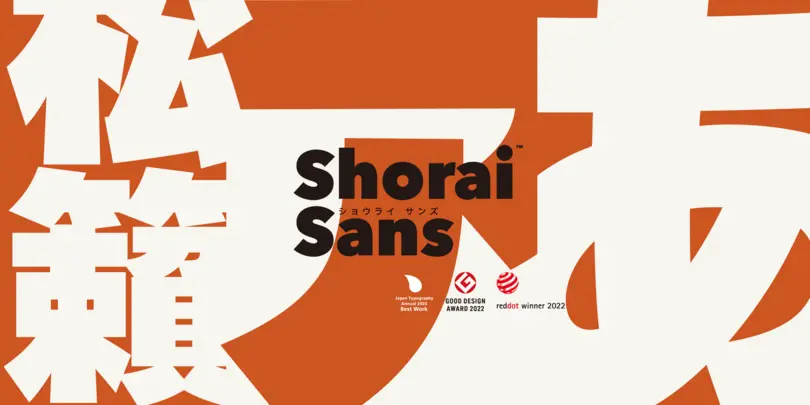
Shorai Sans:何も足さない「素」のかたち
Avenir Nextと調和する日本語書体
Shorai Sansは、欧文書体「Avenir Next」の造形的な特徴を取り入れて開発された日本語サンセリフ体です。「何も足さない『素』のかたち」をコンセプトに、文字の骨格を極限まで単純化し、均一な線とすっきりとした形状を追求しました。幾何学的な美しさを持ちながらも、人の手で書いたような自然な温かみを感じさせるデザインが特徴です。
付属欧文には、日本語の文字に合わせてサイズや位置を調整したAvenir Nextを採用。和文と欧文を別々に選ぶ必要がなく、Shorai Sansだけでバランスの取れた美しい文章を組むことができます。
極細から超極太まで、幅広い表現に対応
Shorai Sansは、Ultra LightからHeavyまでの10ウェイトを展開しています。特に最も太いHeavyでは、複雑な漢字の輪郭線を整理し、文字の内側の空間を確保することで、力強さと読みやすさの両立を目指しました。
また、バリアブルフォントにも対応し、ウェイト間の太さを柔軟に調整できます。印刷物や広告、Webサイト、デジタルデバイスの画面表示、サインなど、用途やデザインに応じた多彩な表現が可能です。
文字の魅力を体感できる見本帳
Shorai Sansの見本帳は、ブックデザイナーの祖父江慎氏がデザインを担当しました。文字の造形をじっくり観察できるよう、画数の多い漢字と少ない漢字、特徴的なひらがなやカタカナを組み合わせて紹介しています。
さらに、10種類のウェイトを比較できる構成や、文字の大きさと太さの関係を視覚的に伝える工夫も盛り込まれています。
本見本帳では、Shorai Sansならではの文字の形やウェイトによる印象の違い、和文と欧文の調和などをご覧いただけます。書体選定やデザイン制作の参考資料として、ぜひご活用ください。